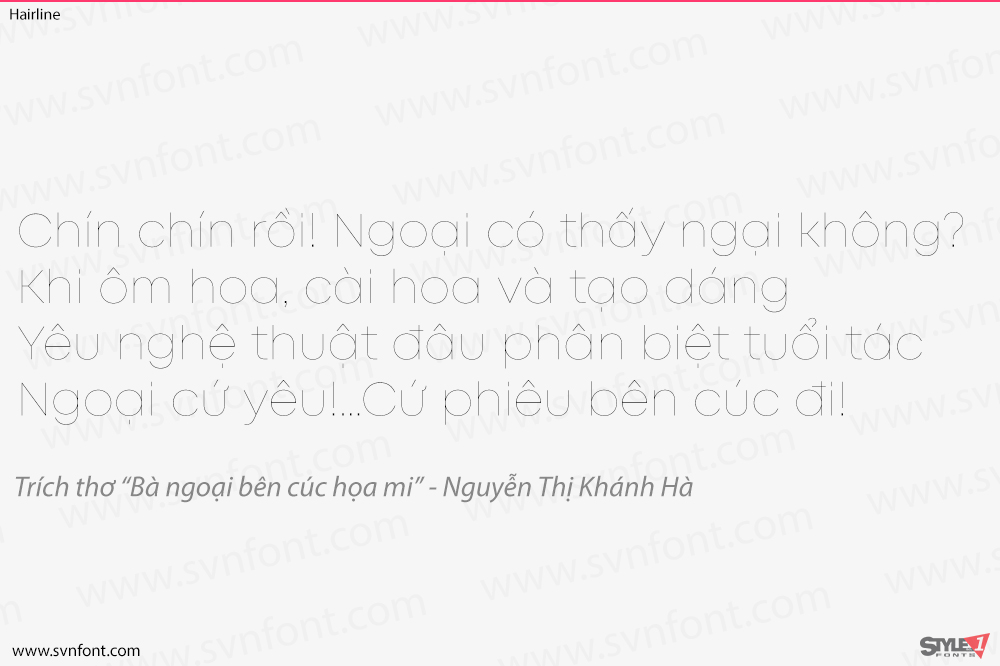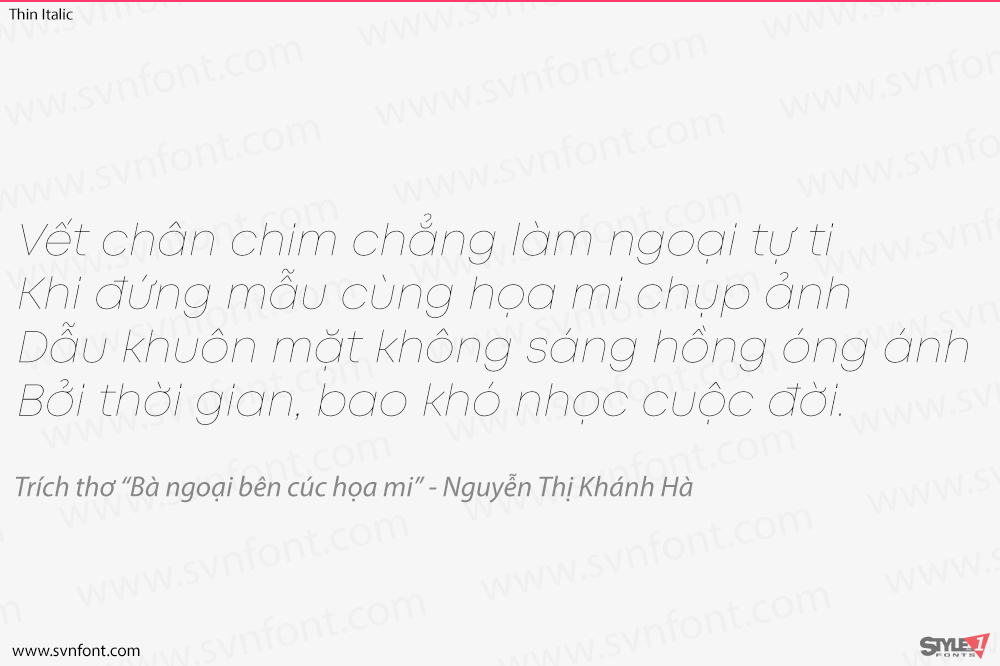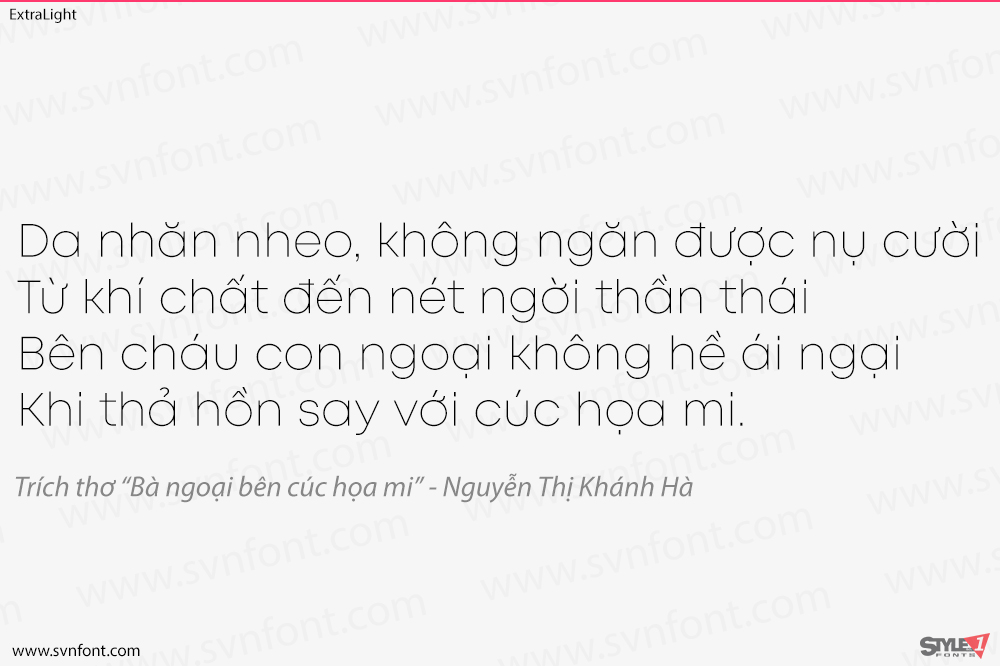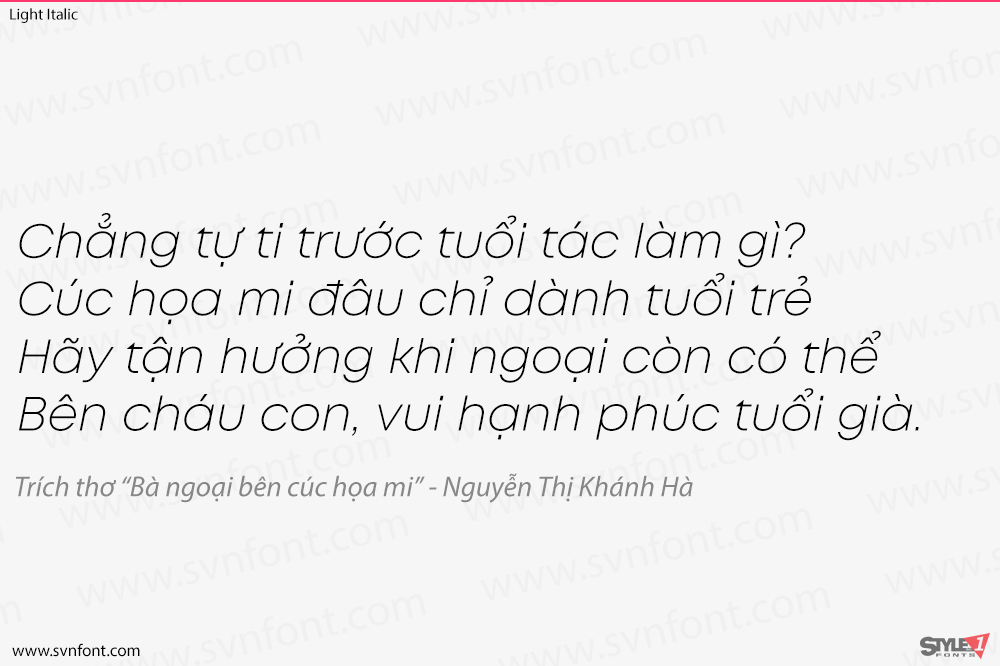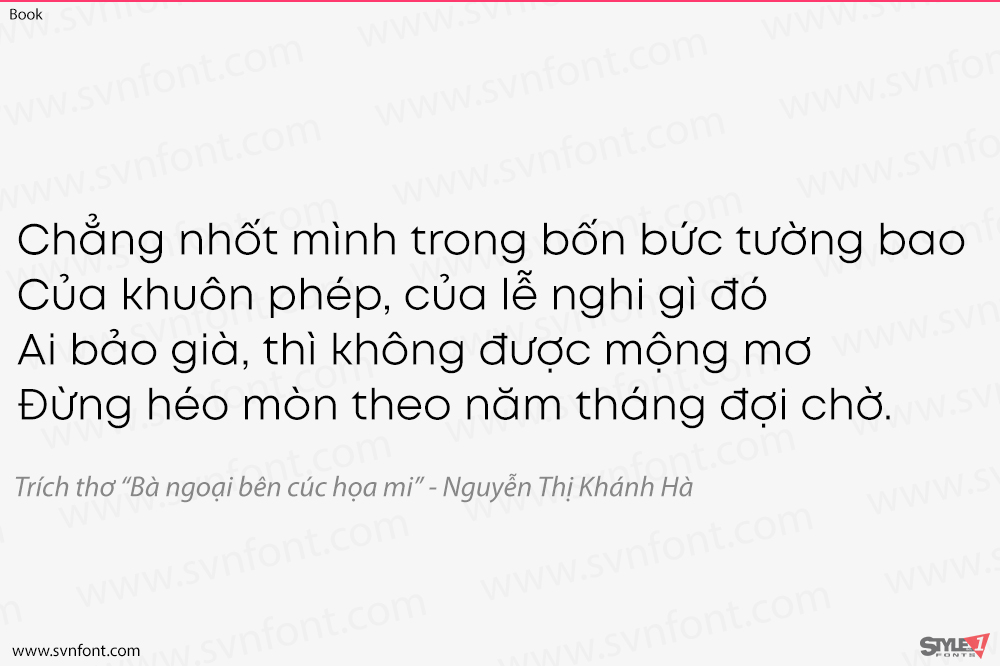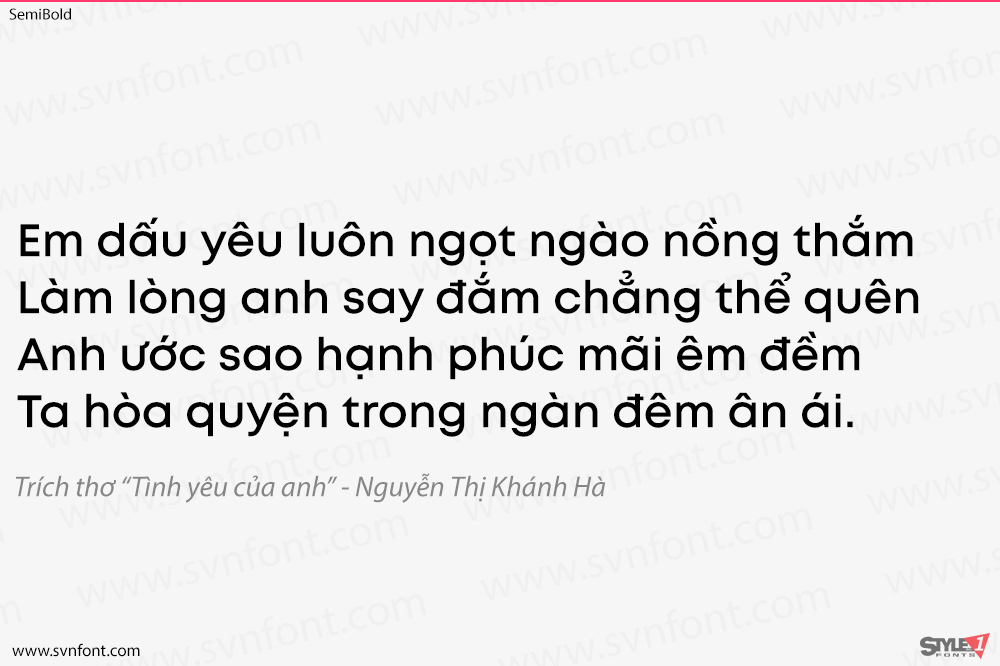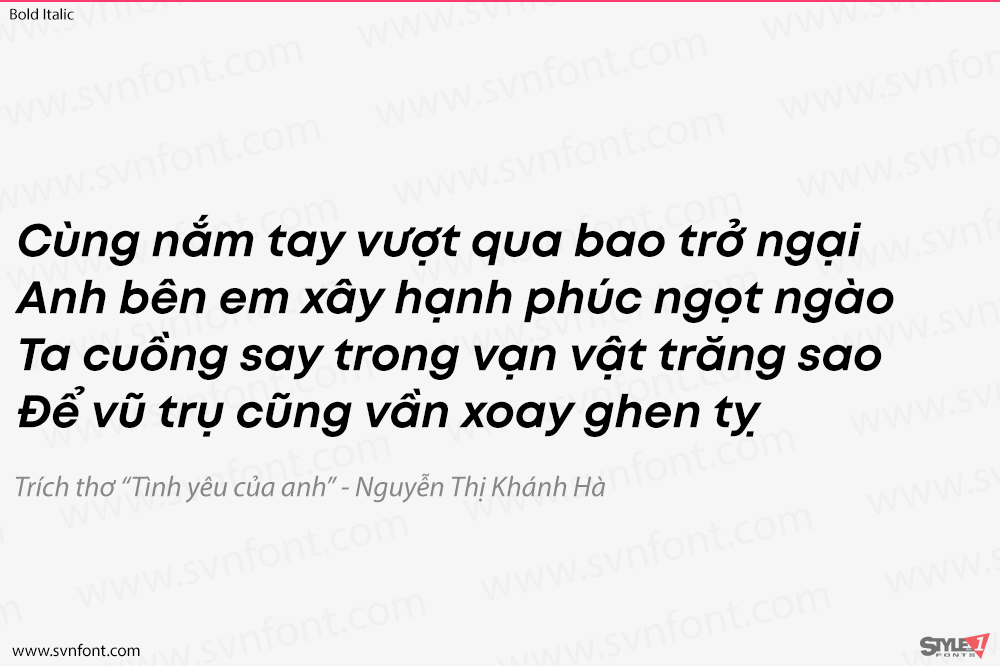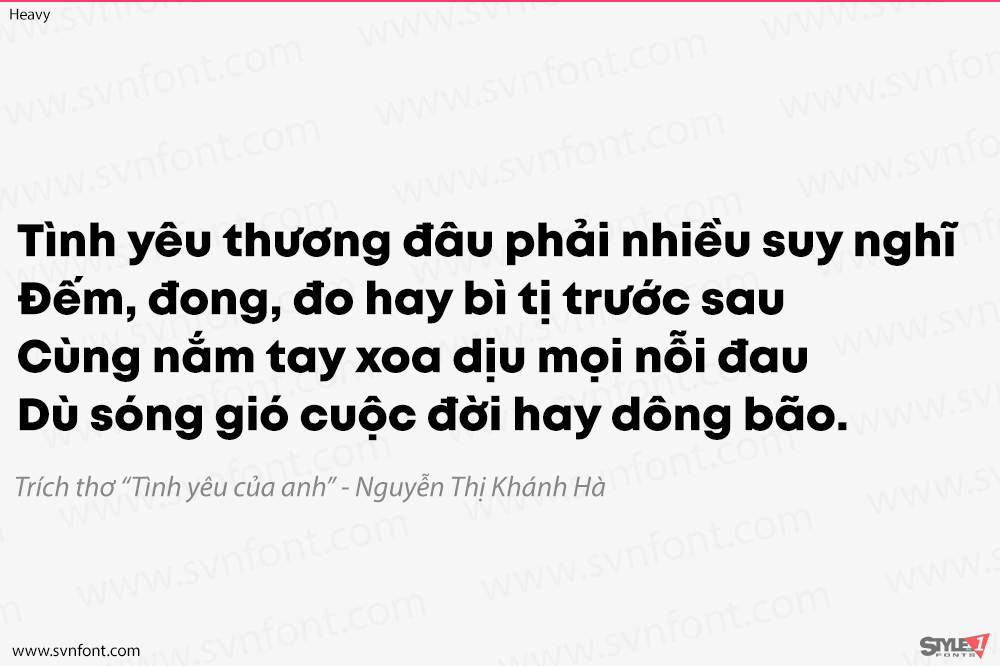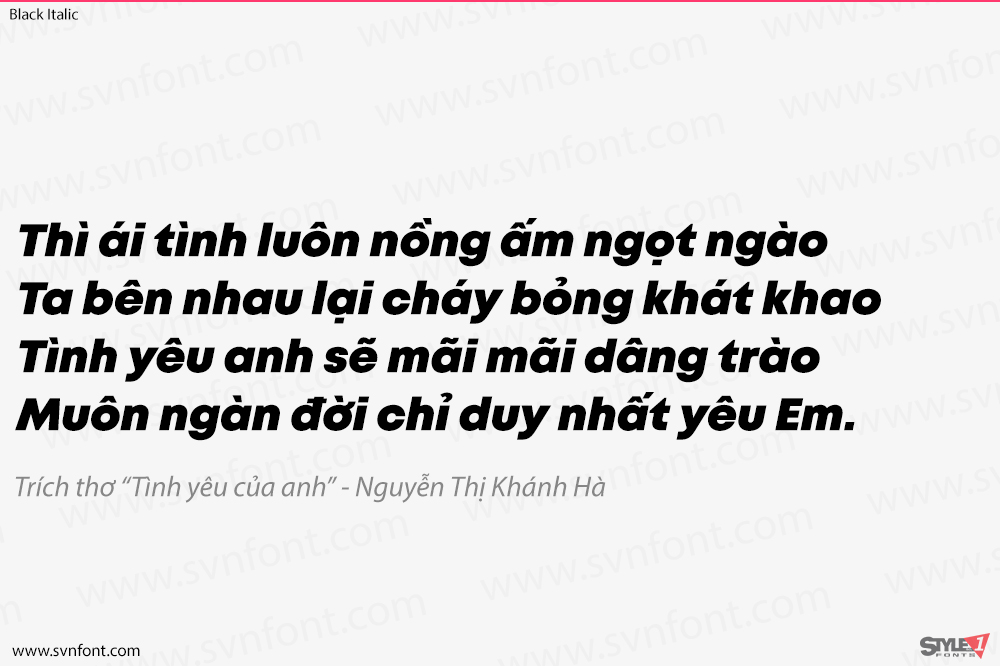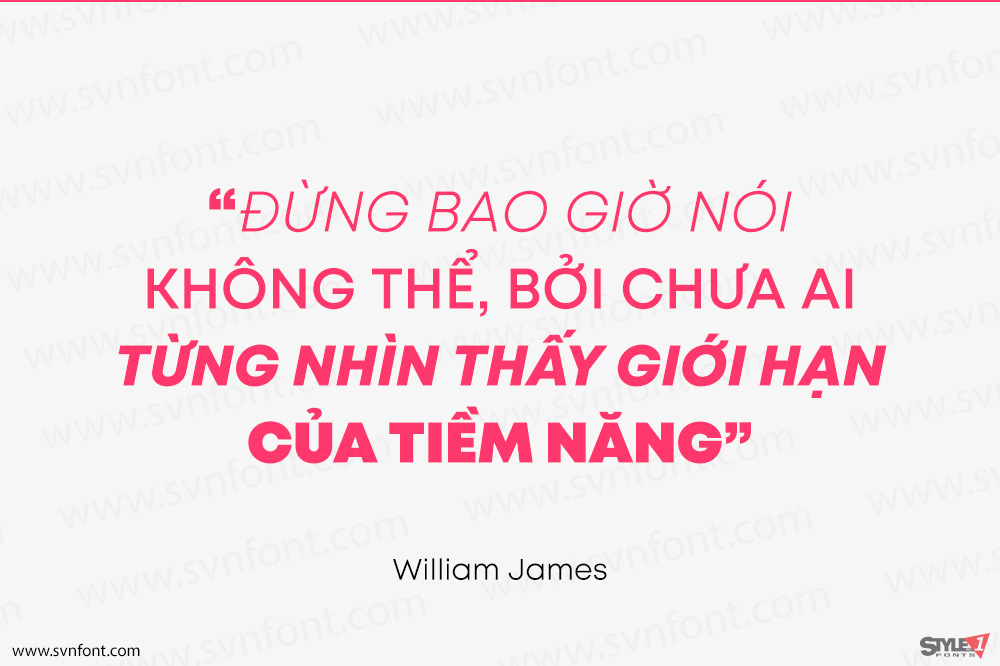
Mont là một kiểu chữ sans serif hình học bao gồm 10 độ dày khác nhau, từ Hairline đến Black, đi kèm với các kiểu chữ nghiêng tương ứng. Nó hỗ trợ bộ ký tự Latin mở rộng, Cyrillic và Hy Lạp — tổng cộng hơn 130 ngôn ngữ. Đặc điểm cân đối của Mont với những chi tiết độc đáo, như chữ “t” nhọn và chiều cao x nổi bật, làm cho nó trở nên hoàn hảo cho các tiêu đề mạnh mẽ và logo ấn tượng, nhưng cũng rất phù hợp cho các đoạn văn bản dài.
Mont đi kèm với một loạt các tính năng OpenType — bao gồm số liệu dạng bảng (tabular figures), các tính năng typographic nâng cao như nối chữ (ligatures), phân số, các dạng chữ phân biệt chữ hoa/thường, chỉ số trên (superscripts), chỉ số dưới (subscripts), v.v. Sự linh hoạt và giá trị của kiểu chữ này giúp dễ dàng đối phó với mọi thách thức trong thiết kế đồ họa — web, in ấn, đồ họa chuyển động, v.v.
Nhà thiết kế: Svetoslav Simov, Mirela Belova
Nhà phát hành: Fontfabric